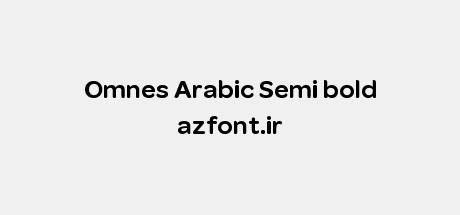
Omnes Arabic Semi bold
فونت زیبای رایگان Omnes Arabic Semi bold
قلم زیبای Omnes Arabic Semi bold از سری قلم های بسیار زیبا برای تایپوگرافی و لوگو تایپ می باشد.این قلم در وزن Regular و توسط Monotype Design Team Nadine Chahine and Nizar Qandah طراحی و منتشر شده است.